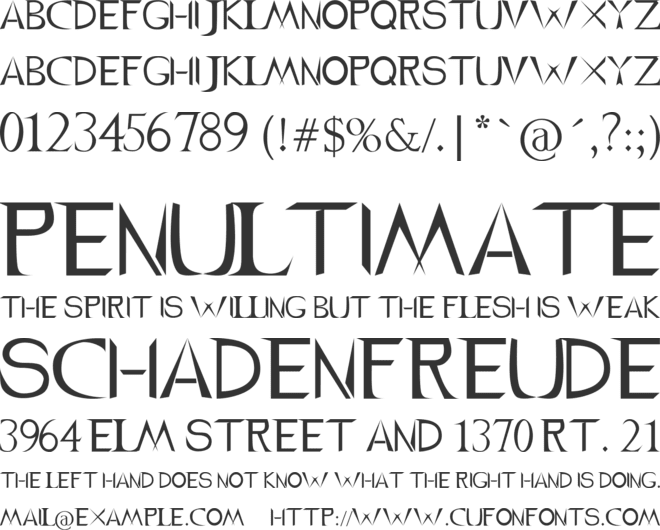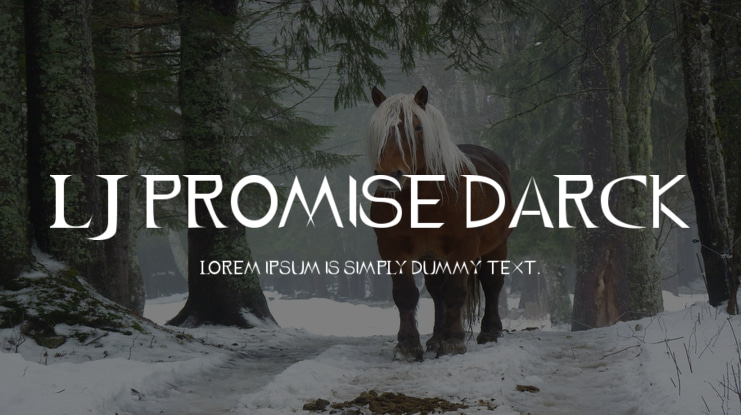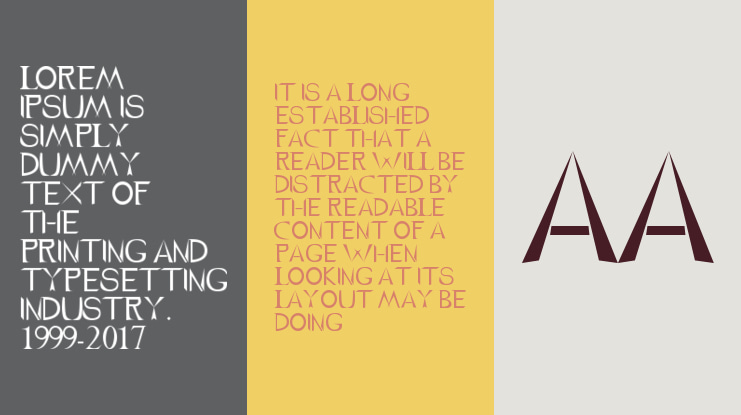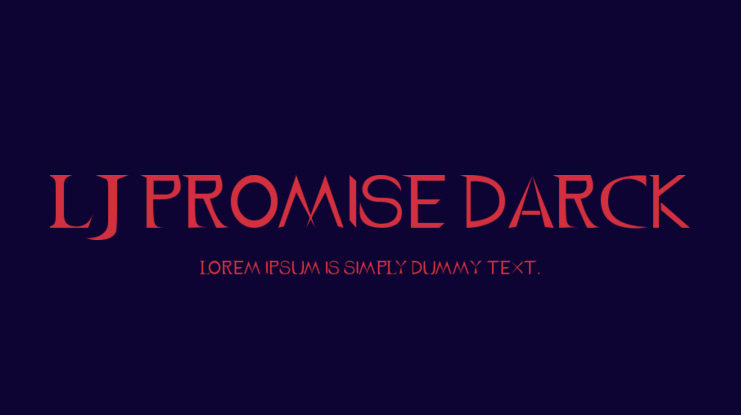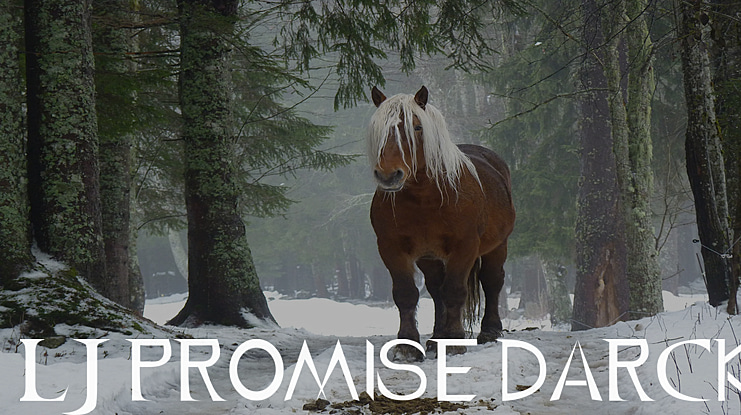
LJ Promise Darck Font
Inspirada en el Hard rock y Rock Pop, su propósito es expresión de lo que sientes.
Ideal para diseños que expresen agresión o sentimientos profundos (Covers Music).